ฟอนต์มีผล! เลือกฟอนต์สร้างแบรนด์ SME ยังไงให้ปัง
การออกแบบตัวอักษร หรือ Typography เป็นมากกว่าแค่การเลือกตัวอักษรที่สวยงาม แต่เป็นเครื่องมือสำคัญในการสื่อสารตัวตนของแบรนด์ โดยเฉพาะสำหรับธุรกิจขนาดกลางและขนาดย่อม (SME) ที่ต้องสร้างความน่าจดจำในตลาดที่มีการแข่งขันสูง ฟอนต์ที่เลือกใช้จะกลายเป็น “เสียง” ที่มองเห็นได้ของแบรนด์ ทำหน้าที่ถ่ายทอดบุคลิก ค่านิยม และสร้างความสัมพันธ์ทางอารมณ์กับลูกค้า
ประเด็นสำคัญของการเลือกฟอนต์สำหรับแบรนด์
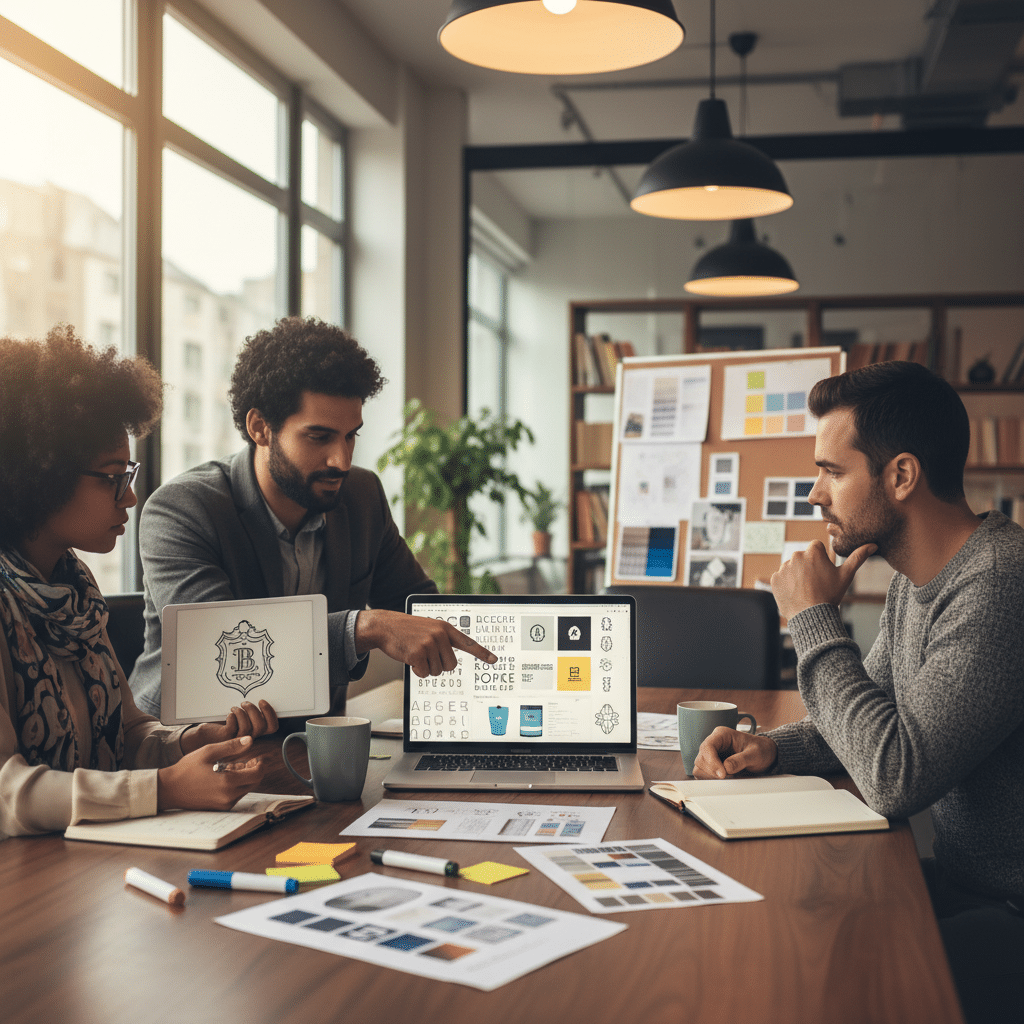
- ความชัดเจนมาก่อนเสมอ: ฟอนต์ต้องอ่านง่ายในทุกขนาดและทุกสื่อ ตั้งแต่โลโก้บนนามบัตรไปจนถึงข้อความบนเว็บไซต์
- สอดคล้องกับบุคลิกแบรนด์: การเลือกใช้ตัวอักษรต้องสะท้อนถึงแก่นแท้และค่านิยมของธุรกิจ ไม่ว่าจะเป็นความน่าเชื่อถือ ความทันสมัย หรือความเป็นกันเอง
- จิตวิทยาของฟอนต์: ฟอนต์แต่ละประเภท เช่น Serif, Sans-serif หรือ Script สามารถกระตุ้นความรู้สึกและการรับรู้ที่แตกต่างกันในกลุ่มเป้าหมาย
- การสร้างเอกลักษณ์: การเลือกและปรับแต่งฟอนต์อย่างมีกลยุทธ์ช่วยให้แบรนด์โดดเด่นและสร้างความแตกต่างจากคู่แข่งได้
ทำไมฟอนต์จึงเป็นหัวใจสำคัญของการสร้างแบรนด์ SME
ในโลกธุรกิจปัจจุบันที่ผู้บริโภคถูกรายล้อมด้วยข้อมูลและแบรนด์มากมาย การสร้างความประทับใจแรกให้เป็นที่จดจำคือความท้าทายที่สำคัญ ฟอนต์มีผล! เลือกฟอนต์สร้างแบรนด์ SME ยังไงให้ปัง จึงเป็นคำถามเชิงกลยุทธ์มากกว่าแค่เรื่องของความสวยงาม ฟอนต์เปรียบเสมือนเสื้อผ้าที่แบรนด์สวมใส่ มันสามารถบอกเล่าเรื่องราว สร้างบรรยากาศ และกำหนดทิศทางการรับรู้ของลูกค้าได้ทันที การเลือกฟอนต์ที่เหมาะสมจะช่วยเสริมสร้างความน่าเชื่อถือ สื่อสารความเป็นมืออาชีพ และทำให้แบรนด์เข้าถึงกลุ่มเป้าหมายได้อย่างแม่นยำ ในทางกลับกัน การเลือกฟอนต์ที่ไม่สอดคล้องกันอาจสร้างความสับสนและบั่นทอนภาพลักษณ์ที่ต้องการสร้างขึ้นมาได้
ฟอนต์ที่ดีต้องสามารถทำงานได้อย่างมีประสิทธิภาพในทุกบริบท ตั้งแต่ขนาดเล็กบนฉลากสินค้าไปจนถึงขนาดใหญ่บนป้ายโฆษณา ความสามารถในการอ่าน (Readability) และความชัดเจน (Legibility) จึงเป็นปัจจัยพื้นฐานที่ต้องพิจารณาเป็นอันดับแรก การเลือกฟอนต์ที่ซับซ้อนหรือตกแต่งมากเกินไปอาจดูน่าสนใจในตอนแรก แต่หากทำให้ลูกค้าอ่านข้อความได้ยาก ก็เท่ากับว่าการสื่อสารนั้นล้มเหลว ดังนั้น การสร้างสมดุลระหว่างความสวยงามและฟังก์ชันการใช้งานจึงเป็นกุญแจสำคัญสู่ความสำเร็จ
ฟอนต์มีผล! เลือกฟอนต์สร้างแบรนด์ SME ยังไงให้ปัง
การเลือกฟอนต์สำหรับแบรนด์ไม่ใช่กระบวนการที่ขึ้นอยู่กับความชอบส่วนตัว แต่ต้องอาศัยหลักการและการวิเคราะห์เพื่อให้ได้ผลลัพธ์ที่ดีที่สุด การตัดสินใจเชิงกลยุทธ์นี้จะส่งผลต่อทุกองค์ประกอบของแบรนด์ ตั้งแต่โลโก้ สื่อสิ่งพิมพ์ ไปจนถึงช่องทางดิจิทัล
ความชัดเจนในการสื่อสารต้องมาก่อน
หลักการข้อแรกและสำคัญที่สุดคือความชัดเจน ฟอนต์ที่เลือกต้องอ่านง่ายในทุกสถานการณ์ ไม่ว่าจะปรากฏบนหน้าจอสมาร์ทโฟน ฉลากสินค้าขนาดเล็ก หรือป้ายบิลบอร์ดขนาดใหญ่ ก่อนจะพิจารณาถึงบุคลิกหรือสไตล์ ควรทดสอบฟอนต์ในขนาดและรูปแบบต่างๆ เพื่อให้แน่ใจว่าข้อความที่ต้องการสื่อสารจะไปถึงผู้รับได้อย่างครบถ้วนและไม่ผิดเพี้ยน
คำแนะนำจากผู้เชี่ยวชาญด้านการพิมพ์เน้นย้ำว่า “ควรให้ความสำคัญกับความสามารถในการอ่าน (Readability) ก่อนบุคลิกของฟอนต์เสมอ”
สะท้อนบุคลิกและแก่นแท้ของแบรนด์
ฟอนต์คือเครื่องมือในการถ่ายทอดบุคลิกของแบรนด์ ธุรกิจที่ต้องการสื่อถึงความหรูหราและคุณภาพสูงอาจเลือกใช้ฟอนต์ประเภท Serif ที่มีความคลาสสิกและสง่างาม ในขณะที่บริษัทเทคโนโลยีที่เน้นนวัตกรรมและความทันสมัยอาจเหมาะกับฟอนต์ Sans-serif ที่ดูเรียบง่ายและสะอาดตา การเลือกฟอนต์ต้องเริ่มต้นจากการทำความเข้าใจแก่นแท้หรือ “Why” ของธุรกิจ เพื่อให้ตัวอักษรสามารถสะท้อนค่านิยมหลักของแบรนด์ออกมาได้อย่างแท้จริง
เชื่อมโยงกับกลุ่มเป้าหมาย
นอกจากการสะท้อนตัวตนของแบรนด์แล้ว ฟอนต์ยังต้องสามารถสื่อสารและเชื่อมโยงกับกลุ่มเป้าหมายได้อีกด้วย ควรพิจารณาว่าต้องการให้ลูกค้ารู้สึกอย่างไรเมื่อเห็นแบรนด์ หากเป็นสินค้าสำหรับเด็ก ฟอนต์ที่มีลักษณะโค้งมนและดูเป็นมิตรอาจเหมาะสมกว่า ในขณะที่บริการทางการเงินที่ต้องการสร้างความน่าเชื่อถือ อาจต้องใช้ฟอนต์ที่ดูมั่นคงและเป็นทางการ การทำความเข้าใจความคาดหวังและรสนิยมของกลุ่มเป้าหมายจะช่วยให้การเลือกฟอนต์มีประสิทธิภาพมากยิ่งขึ้น
สร้างความแตกต่างและเป็นที่จดจำ
ในตลาดที่มีการแข่งขันสูง การสร้างความแตกต่างเป็นสิ่งจำเป็น การเลือกใช้ฟอนต์ที่แตกต่างจากคู่แข่งสามารถช่วยให้แบรนด์เป็นที่จดจำได้ง่ายขึ้น อาจเป็นการเลือกใช้ฟอนต์ที่ไม่เป็นที่นิยมมากนัก หรือการปรับแต่งฟอนต์ที่มีอยู่ให้มีเอกลักษณ์เฉพาะตัว นอกจากนี้ การใช้ฟอนต์คู่กัน (Font Pairing) อย่างมีหลักการ โดยใช้ฟอนต์หนึ่งสำหรับหัวข้อ (Headline) และอีกฟอนต์สำหรับเนื้อหา (Body Text) ก็เป็นเทคนิคที่ช่วยสร้างลำดับชั้นทางสายตาและเพิ่มความน่าสนใจให้กับงานออกแบบได้เป็นอย่างดี
จิตวิทยาของฟอนต์: ถอดรหัสความรู้สึกผ่านตัวอักษร
Font Psychology หรือจิตวิทยาของฟอนต์ คือการศึกษาว่ารูปแบบของตัวอักษรส่งผลต่อการรับรู้ ความคิด และอารมณ์ของผู้คนอย่างไร ฟอนต์แต่ละประเภทมีโครงสร้างและลักษณะเฉพาะที่สามารถกระตุ้นความรู้สึกที่แตกต่างกันโดยไม่รู้ตัว การทำความเข้าใจในหลักการนี้จะช่วยให้ SME สามารถเลือกใช้ฟอนต์เพื่อชี้นำการรับรู้ของลูกค้าให้สอดคล้องกับภาพลักษณ์ที่ต้องการสร้างได้
จากงานวิจัยของ Monotype พบว่าฟอนต์ประเภทต่างๆ มีผลกระทบต่อการรับรู้ของแบรนด์อย่างมีนัยสำคัญ:
| ประเภทฟอนต์ | ความรู้สึกที่สื่อ | ตัวอย่างและผลกระทบ |
| Serif (มีเชิง) | คลาสสิก, น่าเชื่อถือ, คุณภาพสูง, เป็นทางการ | ฟอนต์ Cotford Display Regular สามารถเพิ่มความรู้สึกผูกพันได้ 14%, ความน่าจดจำ 10%, และความน่าเชื่อถือ 9% เหมาะสำหรับแบรนด์แฟชั่นหรู, ธุรกิจที่ปรึกษา หรือสถาบันการเงิน |